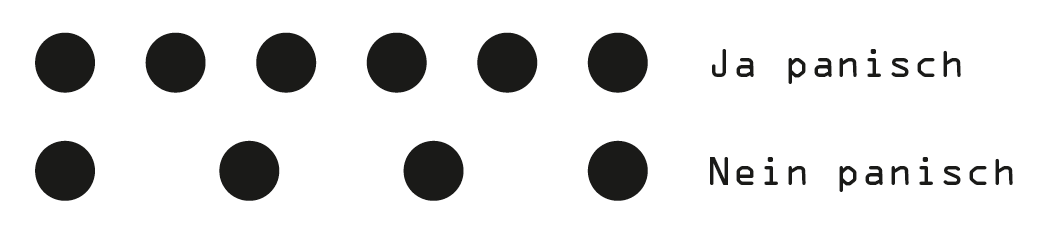
Japanische Punkte
Was mich schon immer interessiert hat: Was sind "Japansche Punkte"? ;-)
Eine Erfindung von Adobe? Ich kann hierzu historisch belegt nichts finden …
Japanische Punkte sind m.W. eher Kreise; also ein Punkt mit Loch. Ich weiß aber auch nicht genau, wo die genau zu stehen haben, da Japaner ja anscheinend keine Schriftlinie haben, an der sie ihre recht quadratischen Buchstaben ausrichten könnten. Zumal traditionell Japanisch von rechts oben nach links unten geschrieben wird. Vielleicht kann uns ein des japanischen Mächtiger Klarheit verschaffen...?
Pygmalion meint die gepunktete Linie in InDesign, die Adobe mit "japanische Punkte" benannt hat. Die haben nichts mit den japanischen Satzzeichen zu tun.
Genau, diese meine ich. Finde es seltsam nirgendwo Hintergrundwissen darüber zu finden …
Ein Merkmal der japanischen ist, dass der Zwischenraum so groß wie der Punkt selbst ist. Aber warum die dann japanisch heißen?
Also, Ingo hat nicht unrecht: die Bezeichnung der von Adobe mit »Japanische Punkte« benannten Linie in InDesign hat in der Tat mit japanischen Satzzeichen zu tun, und zwar mit Kreisen. So sieht das gleiche Bild von bertel im Japanischen aus:
Und dort steht auf Japanisch: 句点, was nichts anderes bedeutet als der Punkt für das Satzende.
Das interessante dabei ist allerdings, dass der einzelne Punkt der so genannten »Japanischen Punkte« gar kein japanischer Punkt ist, den Japaner verwendet. Im japanischen Internet fragt sich offenbar auch niemand, warum denn diese gepunktete Linie eigentlich so heißt. Möglicherweise wurde die englische Bezeichnung dieser Linie »Japanese Dots« einfach so wortwörtlich übersetzt – auch ins Deutsche.
… die Bezeichnung der von Adobe mit »Japanische Punkte« benannten Linie in InDesign hat in der Tat mit japanischen Satzzeichen zu tun, und zwar mit Kreisen. …
Bleibt aber immer noch die Frage, warum sie so heißen, weil sie ja gar keine sind. Bislang kannte ich den japanischen Full Stop eben nur als Kreis, nie als ausgefüllten Punkt.
Vielen Dank Makoto für die Erklärung. Ich habe gerade noch einmal bei decodeunicode nachgelesen, was dort zum Unicodepunkt U+3002 (IDEOGRAPHIC FULL STOP) steht:
IDEOGRAFISCHER PUNKT: Der Punkt in CJK, also in den Chinesischen, Japanischen und Koreanischen Schriftsystemen.
Geschichte: Nach der Encyclopaedia Britannica verwendete Japan seit 1868 »the solid point«.
Kann also durchaus sein, dass Bertel sich richtig erinnert hat und deswegen den Punkt im Japanischen nur als gefüllten Kreis kennt. Und ich habe mich vielleicht durch den Namen, den die Übersetzer von Adobe für diese grafische Linie gefunden haben, täuschen lassen, als ich meine Antwort geschrieben habe. Diese Übersetzung in InDesign ist in der Tat blöde und irritierend - aber die kennen uns Deutsche mit dieser penetranten Gründlichkeit eben nicht. Wir gucken in jede noch so entlegene Lücke :-)
Jedoch stimmt die Bertlesche Annahme nur zum Teil, denn ein Blick ins japanische Wikipedia lehrt uns, dass entgegen der Encyclopaedia Britannica doch noch (?) der Codepoint U+3002 als Kreisform verwendet wird; im deutschen Wikipedia erfährt dieser Umstand nicht mal eine Erwähnung, obwohl in der entsprechenden Seite zur CJK-Interpunktion das Zeichen korrekt gezeigt wird.
Mithin ist der »reale japanische Punkt« also eher ein ungefüllter als ein gefüllter Kreis und erst recht keine Perlenschnur aus diversen Punkten - egal in welchem Abstand zueinander. Und er wird fleißig in der Realität eingesetzt...
… Kann also durchaus sein, dass Bertel sich richtig erinnert hat und deswegen den Punkt im Japanischen nur als gefüllten Kreis kennt. …
Grad andersrum, lieber Ingo. Ich kenne ihn nur als ungefüllten Kreis :-)
Bleibt aber immer noch die Frage, warum sie so heißen, weil sie ja gar keine sind.
Ja, das stimmt. Da muss man wohl die Entwickler bei Adobe nachfragen. Im Netz gibt es jedenfalls weder auf Japanisch noch auf Englisch einen Treffer. Wir Japaner verstehen gar nicht, warum sie »Japanische Punkte« heißen sollten. Von uns gesehen sind sie ja »europäische Punkte« :lol:
In Japan gibt es allerdings komische Satzregeln und -empfehlungen, die zwar von »oben« kommen aber kaum praktiziert werden. Komma und Punkt in horizontaler Schreibrichtung gehören definitiv dazu:
Ich vermute InDesign verwenden sie die Bezeichnung, weil die Punkte diesen Mittelpunkten sehr ähnlich sind.
Aber wirklich beweisen kann ich diese Vermutung nicht.